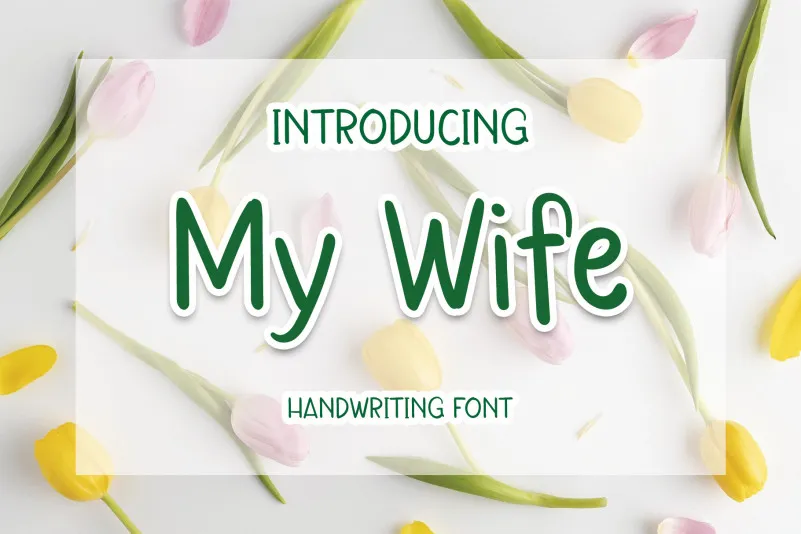
A fonte My Wife oferece uma experiência visual agradável e enriquecedora para quem deseja adicionar um toque descontraído aos seus projetos digitais. Desenvolvida pelo designer Erik Studio, esta font é ideal para criar mensagens de letra cuidadosamente escritas ou estilizadas com personalidade. A My Wife não apenas oferece uma aparência limpa e natural, mas também permite que você personalize sua linguagem digital de maneira divertida e original em aplicações como cartões de presente, design gráfico, marcas de marca, e até mesmo projetos DIY criativos no seu Instagram ou redes sociais. A My Wife é a escolha perfeita para quem busca uma fonte descomplicada que ainda consegue expressar sua personalidade com elegância.